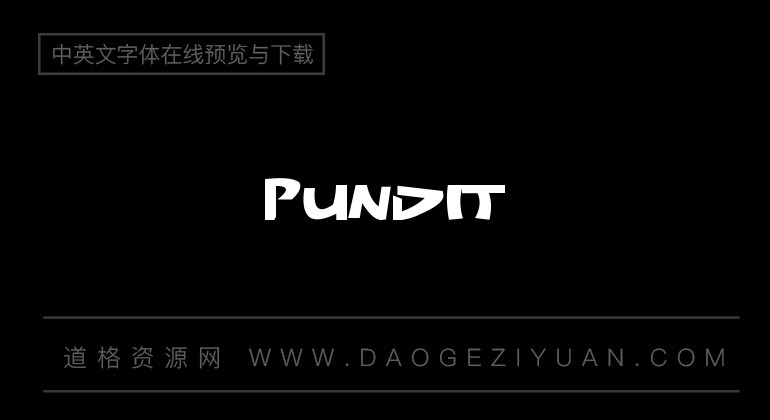
Pundit
Pundit 字体是一种矢量字体,由英国设计师 Alex Haigh 设计,于 2017 年发布。Pundit 字体以简洁明了的线条和锐利的角度设计,具有超强的视觉冲击力,适用于标题、标识、标签等等,是一款非常有用的字体。它的字形设计精细,可以提供清晰的文字排版,而且可以放大到任何尺寸,不会失真。此外,Pundit 字体还支持多种字体格式,如 OpenType、TrueType 等,可以方便地应用于各种设计项目中。
Pundit是一款非常不错的手写艺术字体,具有很好的视觉感,适合于文化类的宣传设计、商业类品牌的广告和产品包装设计以及个性化文字排版等较多场景。